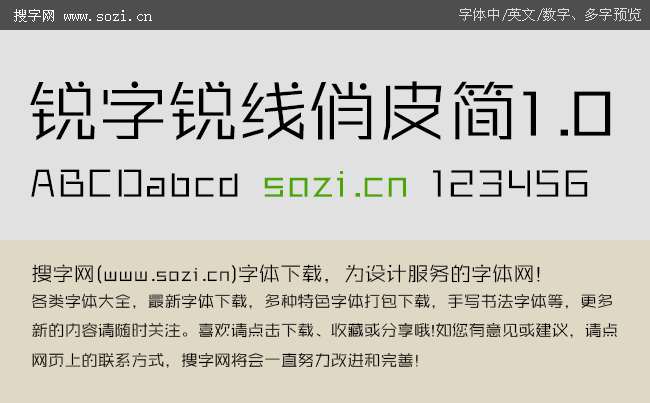
銳字銳線俏皮簡(jiǎn)1.0
搜字網(wǎng)提供一款銳字銳線俏皮簡(jiǎn)1.0中文字體下載,銳字銳線俏皮簡(jiǎn)是一款卡通風(fēng)格的中文藝術(shù)字體,該字體大方得體,俏皮可愛,且字體完整,整體效果非常出眾,適合應(yīng)用于廣告設(shè)計(jì)、名片設(shè)計(jì)、包裝印刷、產(chǎn)品設(shè)計(jì)等應(yīng)用。